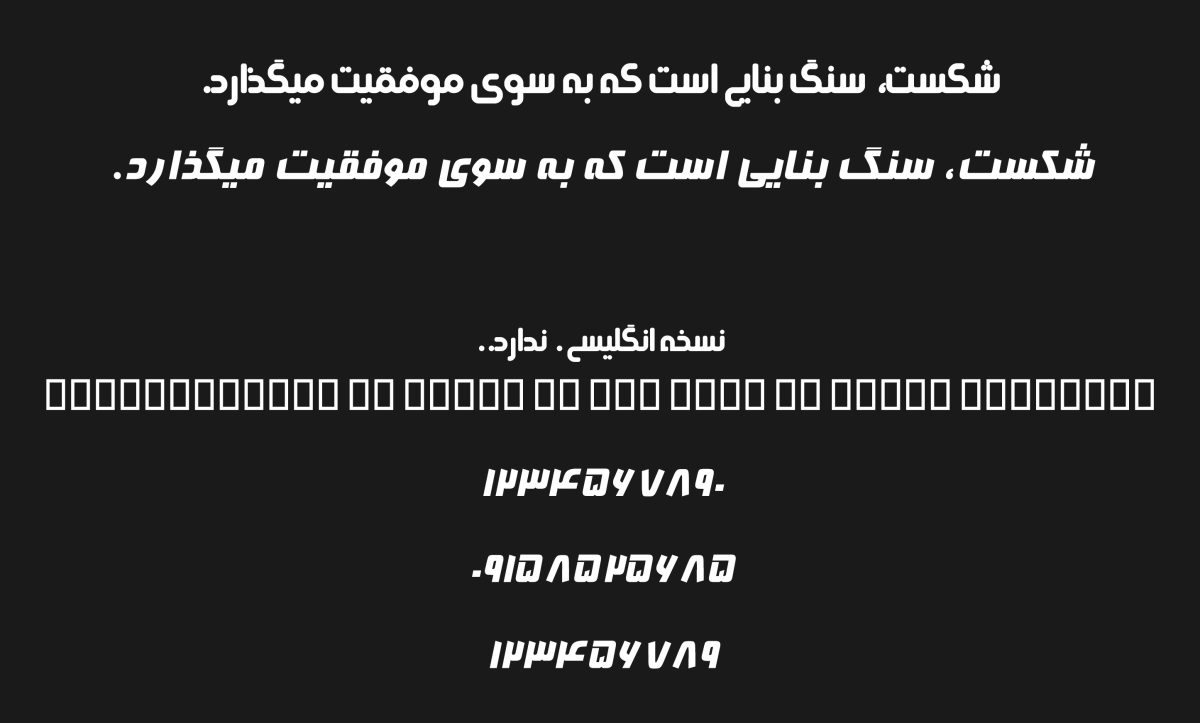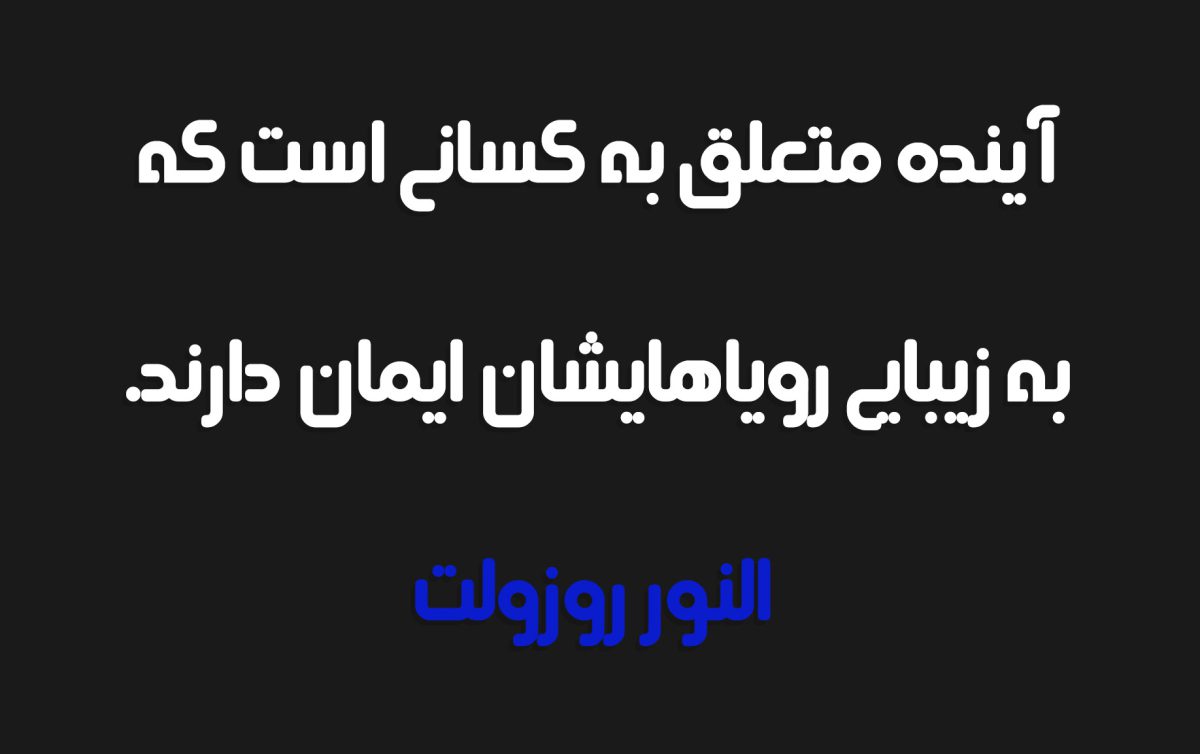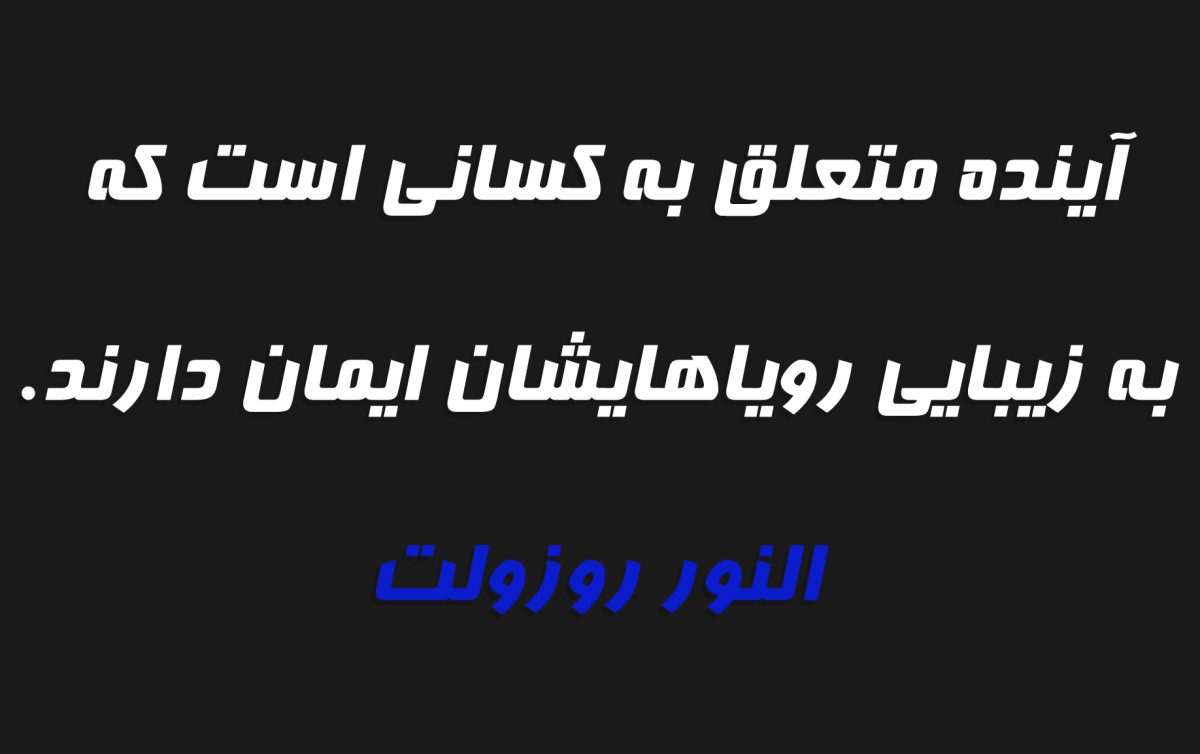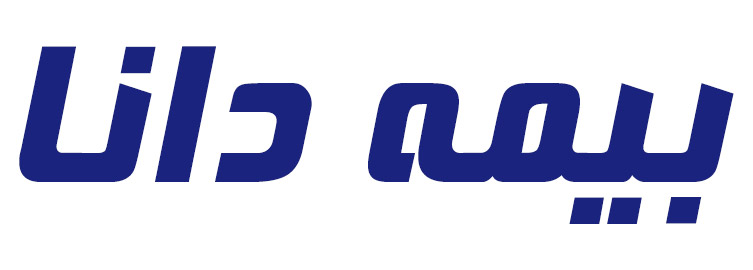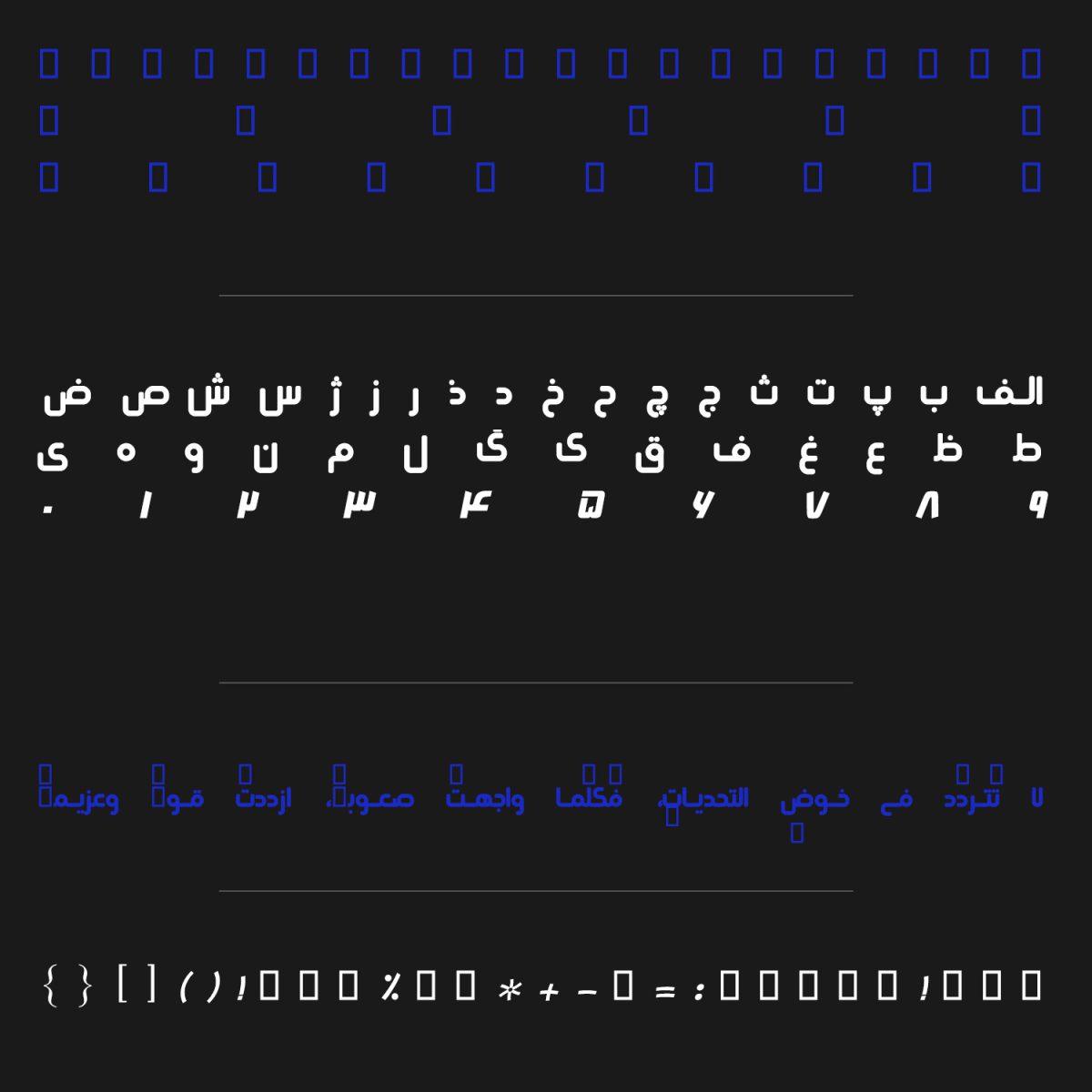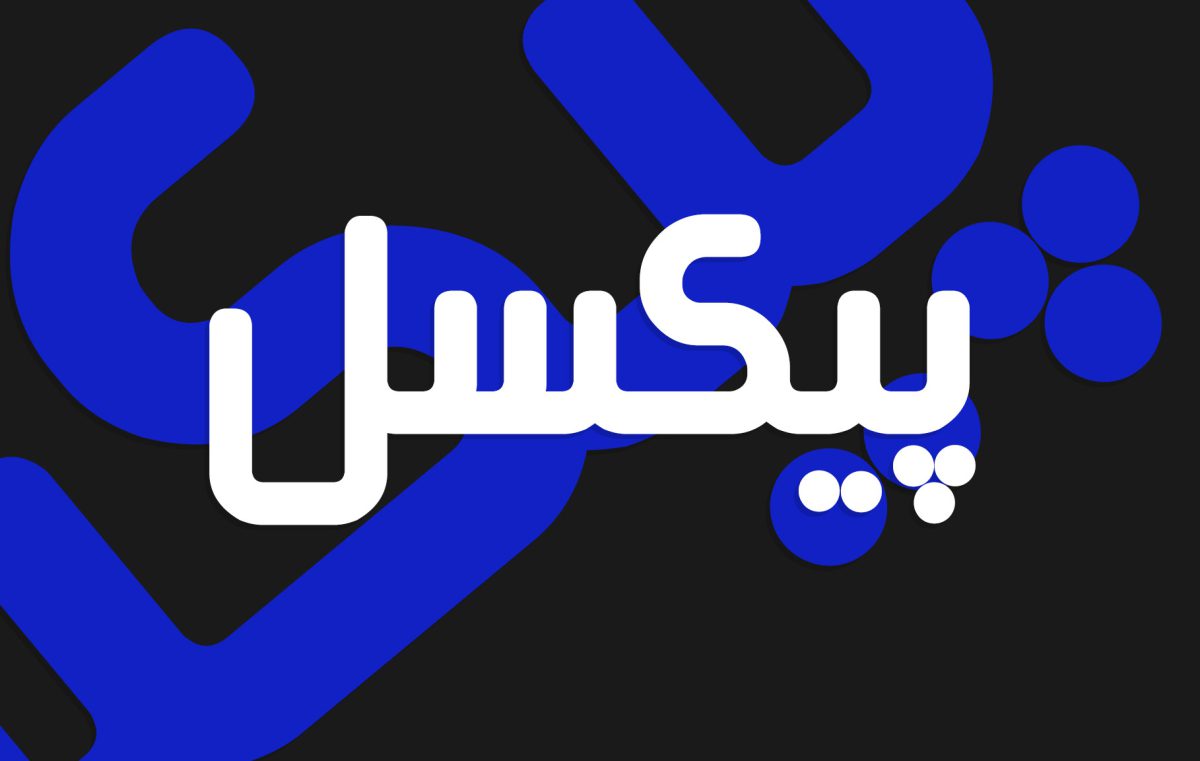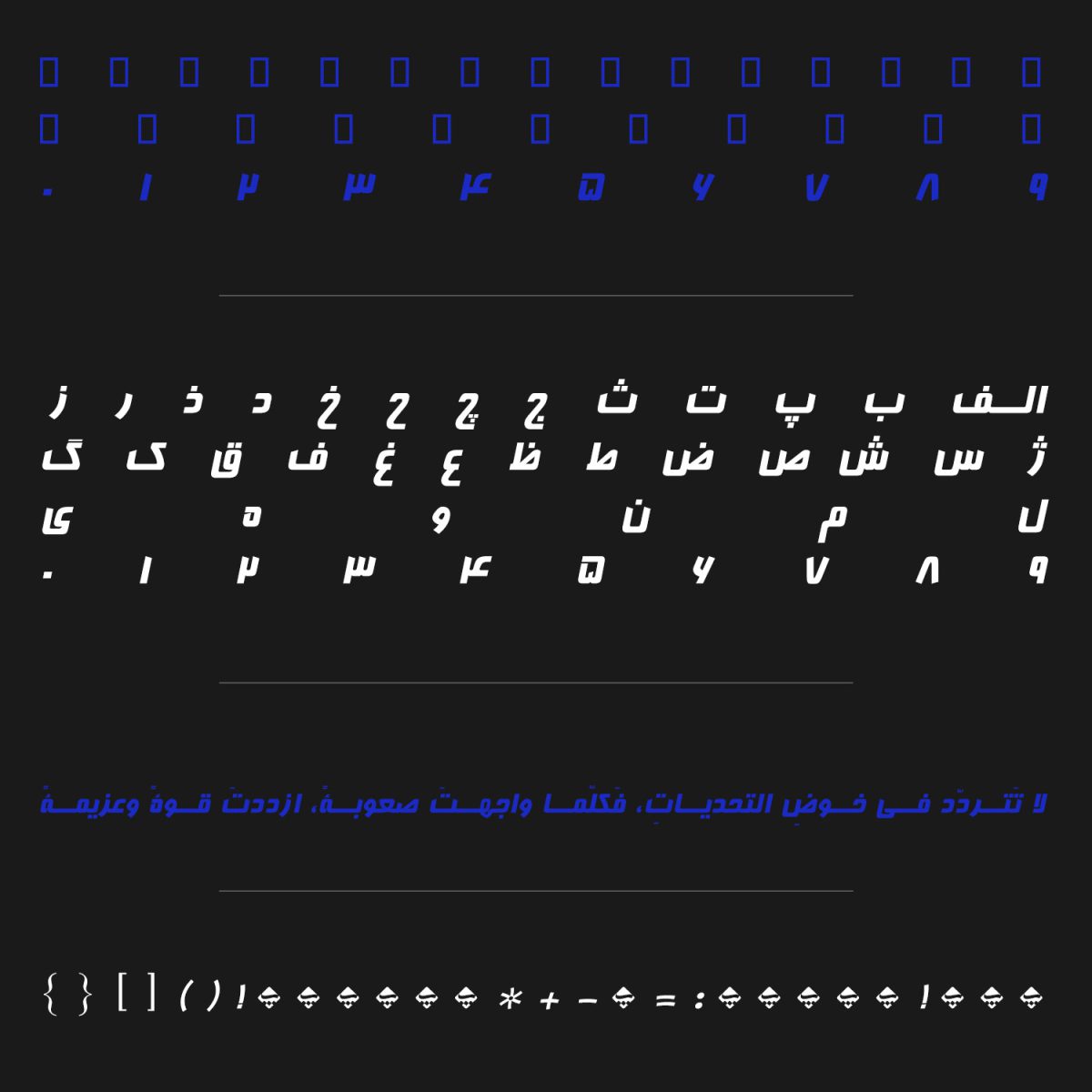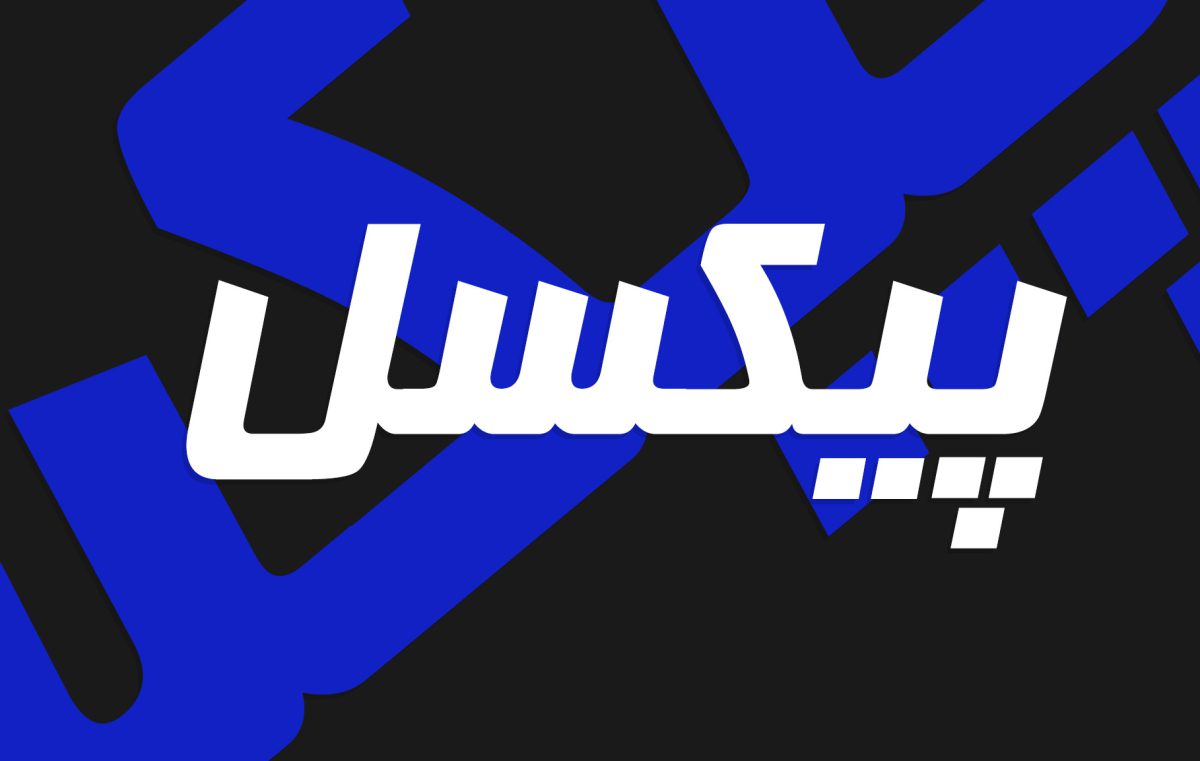
فونت بیمه دانا (Bime Dana)، قلمی پولی، زیبا و حرفه ای فارسی است که با الهام از لوگوتایپ معروف بیمه دانا طراحی شده و اکنون در نسخه سوم بهبود یافته ارائه می شود. این فونت اصلی دارای ساختاری بسیار نرم با گوشه های گرد و نقطه دایره ای است که هم فانتزی و هم رسمی است. نسخه ۳ مشکلات نگارشی حروف گژپچ و جدا نوشتن حروف را حل کرده و علائم و اعداد فارسی را افزوده است. همچنین، فونت اپیک بیمه دانا با گوشه های تیز و نقطه های مربعی و سبکی مشابه اما متفاوت به این مجموعه اضافه شده. این قلم ها برای لوگو، تایپوگرافی و عناوین ایده آل بوده و پس از خرید با فرمت TTF و آپدیت رایگان در دسترس هستند. بدون حروف انگلیسی و یکسری علائم
فونت بیمه دانا: قلم پولی و حرفه ای با نسخه سوم بهبود یافته و فونت اپیک با سبکی متفاوت
فونت بیمه دانا (Bime Dana) یا فونت دانا (Dana)، یک قلم پولی است که با الهام از لوگوتایپ معروف بیمه دانا و با هدف ارائه ابزاری حرفه ای برای طراحی لوگو و عناوین توسعه یافته است. این فونت اصلی دارای ساختار متفاوت و زیبای فونت است که به صورت بسیار نرم طراحی شده و ویژگی خاصی دارد: در عین فانتزی بودن حالت رسمی نیز دارد. این قلم بر وزن بولد | Bold | طراحی شده و به صورت تک وزن (برای فونت اصلی) عرضه می شود.
با نسخه سوم فونت، بهبودهای قابل توجهی اعمال شده است. حروف گژپچ به فونت اضافه شد و مشکل عدم نوشت این حروف در نسخه های قبلی حل گردید. همچنین، جدا نوشتن حروف در برخی برنامه ها نیز حل شد که سازگاری و راحتی استفاده را افزایش می دهد. اضافه شدن یکسری علائم استاندارد و بعلاوه اعداد فارسی به فونت اضافه شد تا پوشش کاراکتری کامل تر شود. این به روزرسانی ها کیفیت و کشش بالای فونت را تضمین می کنند.
دانلودنکته قابل توجه دیگر، اضافه شدن فونت اپیک بیمه دانا به این مجموعه است. این فونت دارای سبکی متفاوت با فونت اصلی در عین حا مشابه می باشد. فونت بیمه دانا اصلی با گوشه گرد و نرم با نقطه های دایره ای شناخته می شود، در حالی که اپیک بیمه دانا با گوشه های تیز و نقطه های مربعی طراحی شده است. این تنوع بصری، گزینه های بیشتری را برای طراحان در اختیار قرار می دهد.
کاربردهای فونت بیمه دانا و فونت اپیک در طراحی گرافیک
فونت بیمه دانا و فونت اپیک بیمه دانا، هر دو ابزارهایی قدرتمند برای انواع امور گرافیکی هستند، به خصوص در زمینه هایی که نیاز به قلمی با شخصیت قوی و متمایز وجود دارد. این قلم ها یکی از زیباترین فونت ها جهت استفاده در لوگو ها و عنوان نویسی هاست.
با الهام از لوگوتایپ بیمه دانا، این فونت ها بهترین گزینه جهت استفاده در عناوین و لوگوها می باشند و به طراحان اجازه می دهند تا با تایپ ساده، لوگوهای حرفه ای خلق کنند. آن ها برای طراحی لوگوتایپ و تایپوگرافی در طرح های گرافیکی مختلف مانند پوسترها، بنرها، کارت ویزیت ها و استفاده در وب سایت ها (برای عنوان ها) مناسب هستند. تنوع میان فونت بیمه دانا اصلی با گوشه های گرد و فونت اپیک با گوشه های تیز، گزینه های بصری بیشتری را برای انطباق با هویت برند فراهم می آورد. استفاده از آن ها در نرم افزارهای گرافیکی حرفه ای توصیه می شود.